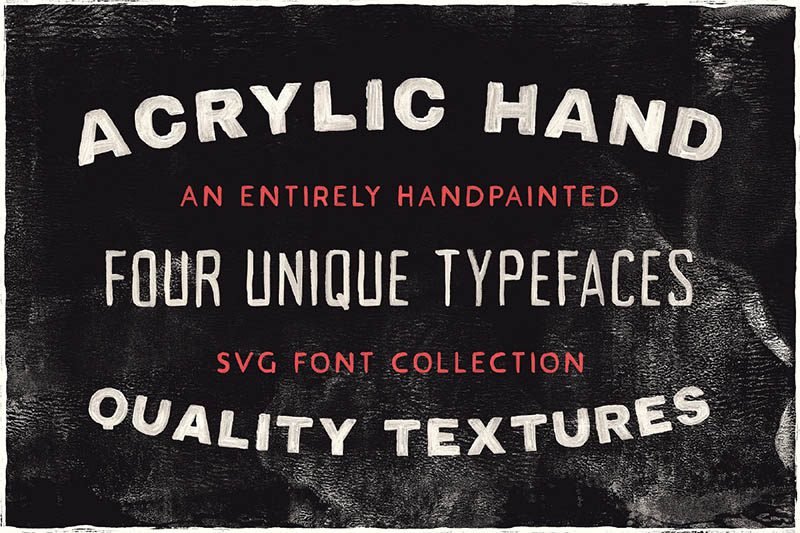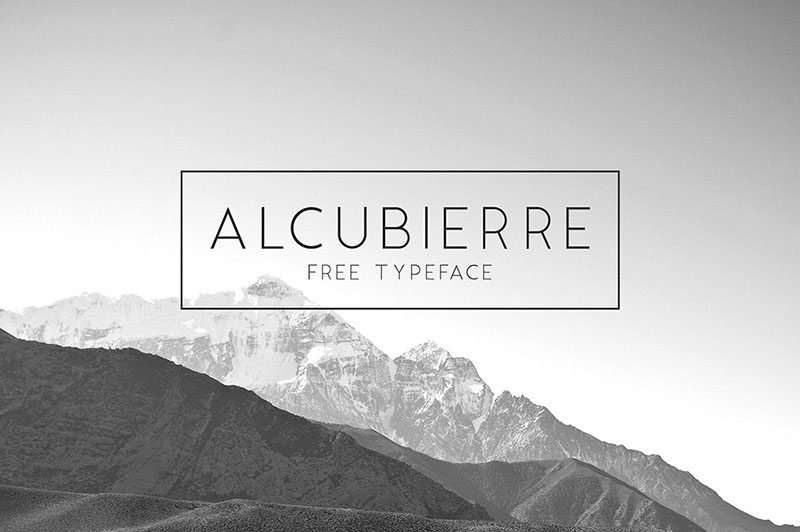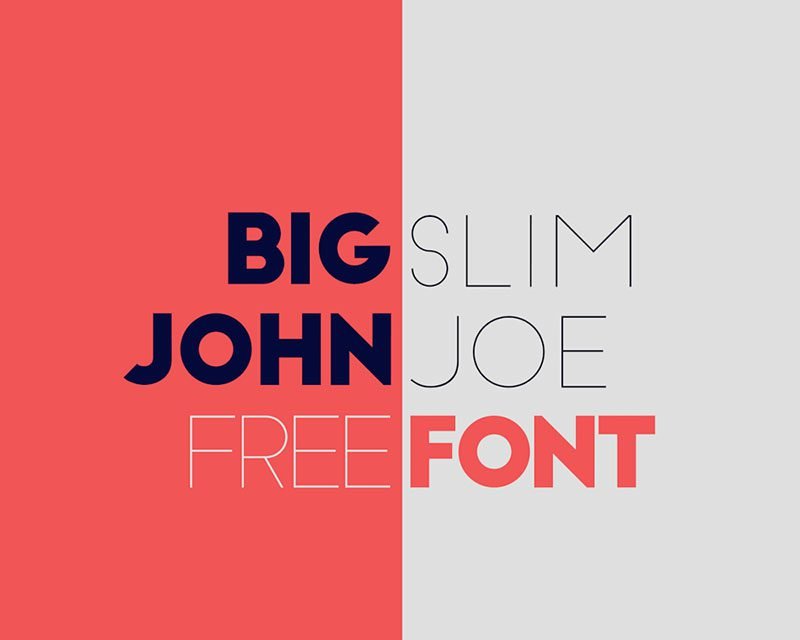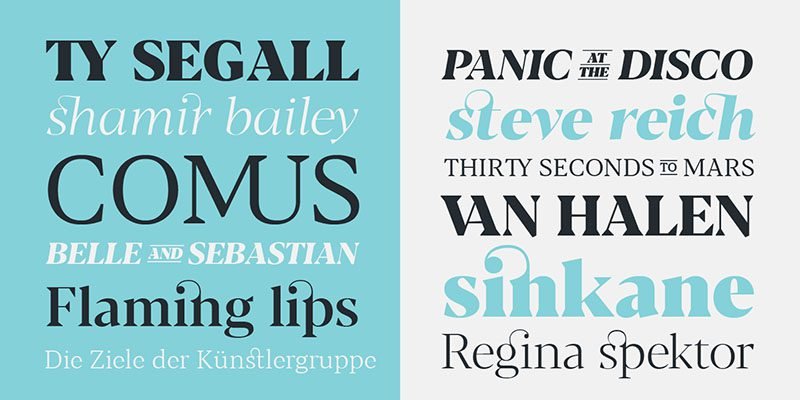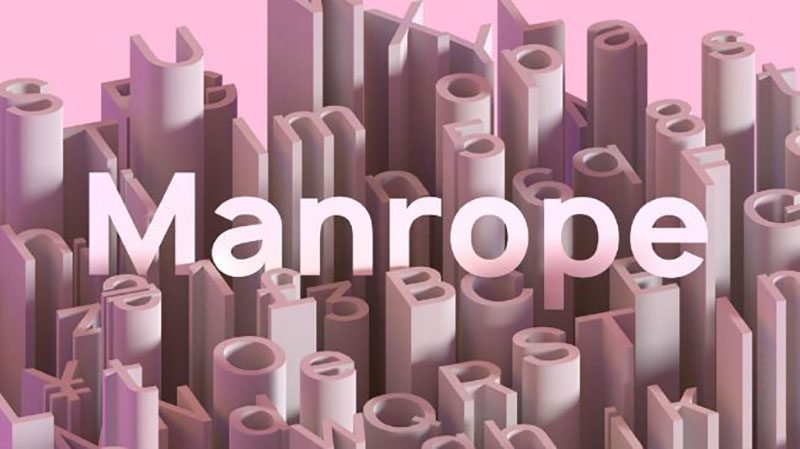
Cinco tipografías para descargar en forma gratuita
Recursos disponibles online
Accesibles para diseñadores y aficionados, internet es el medio a través del cual muchos profesionales comparten sus fuentes tipográficas para que otros usuarios puedan descargarlas en forma gratuita. Serif, sans-serif, script o decorativas, la cantidad de diseños es amplia, es por eso que, a continuación, seleccionamos cinco fuentes para tener en cuenta al llevar adelante cualquier proyecto creativo.
Blacker, de Cosimo Lorenzo Pancini y Andrea Tartarelli
Blacker ha sido diseñada por Cosimo Lorenzo Pancini y Andrea Tartarelli, se trata de una tipografía serif con alto contraste, agrupada en dos familias. La primera, una variante para pantalla, que ofrece un kern más estrecho, un mayor contraste y esquinas más nítidas para alcanzar un mejor efecto en tamaños grandes. La segunda es la variante de texto, ideada para mayor legibilidad. Cada una incluye seis densidades diferentes y el formato itálica. Para descargar Blacker, haz click aquí.
Manrope, de Michael Sharanda
Parte de una familia de fuentes de código abierto, Manrope ha sido diseñada por Michael Sharanda. Disponible en siete estilos, esta tipografía funciona en títulos y párrafos, tanto en formato impreso, como web. Sin cursiva disponible, su creador considera que no es necesaria, abarca la mayoría de las lenguas latinas y cirílicas. A su vez, tiene la capacidad de modificarse automáticamente entre comillas. Para descargar Manrope, haz click aquí.
Alcubierre, de Matt Ellis
Esta tipografía presenta un estilo geométrico sans serif. Su carácter minimalista ha sido diseñado por el inglés Matt Ellis, inspirado en el trabajo desarrollado anteriormente para su fuente Ikaros. Las líneas simples y limpias de sus caracteres permiten un uso variado, que funciona a la perfección en cualquier tipo de formato. Para descargar Alcubierre, haz click aquí.
Big John – Slim Joe, de Ion Lucin
Este dúo tipográfico presenta un estilo geométrico moderno, que apela a figuras racionales y simples. Creada por Ion Lucin, la combinación de ambas permite crear un contraste perfecto a partir de la yuxtaposición de cualquiera de sus caracteres, para alcanzar un mayor impacto visual. Para descargar Big John – Slim Joe, haz click aquí.
The Acrylic Collection, de Tom Chalky
El diseñador inglés Tom Chalky es el responsable de esta colección de tipografías pintadas a mano en acrílico. Su descarga, disponible en forma gratuita para uso personal y restringida de acuerdo al tipo de uso comercial que se le quiera dar. Incluye cuatro fuentes en vectores, que ofrecen un amplio rango de caracteres. Su diseño manual otorga una sensación de textura y realismo. Para descargar The Acrylic Collection, haz click aquí.